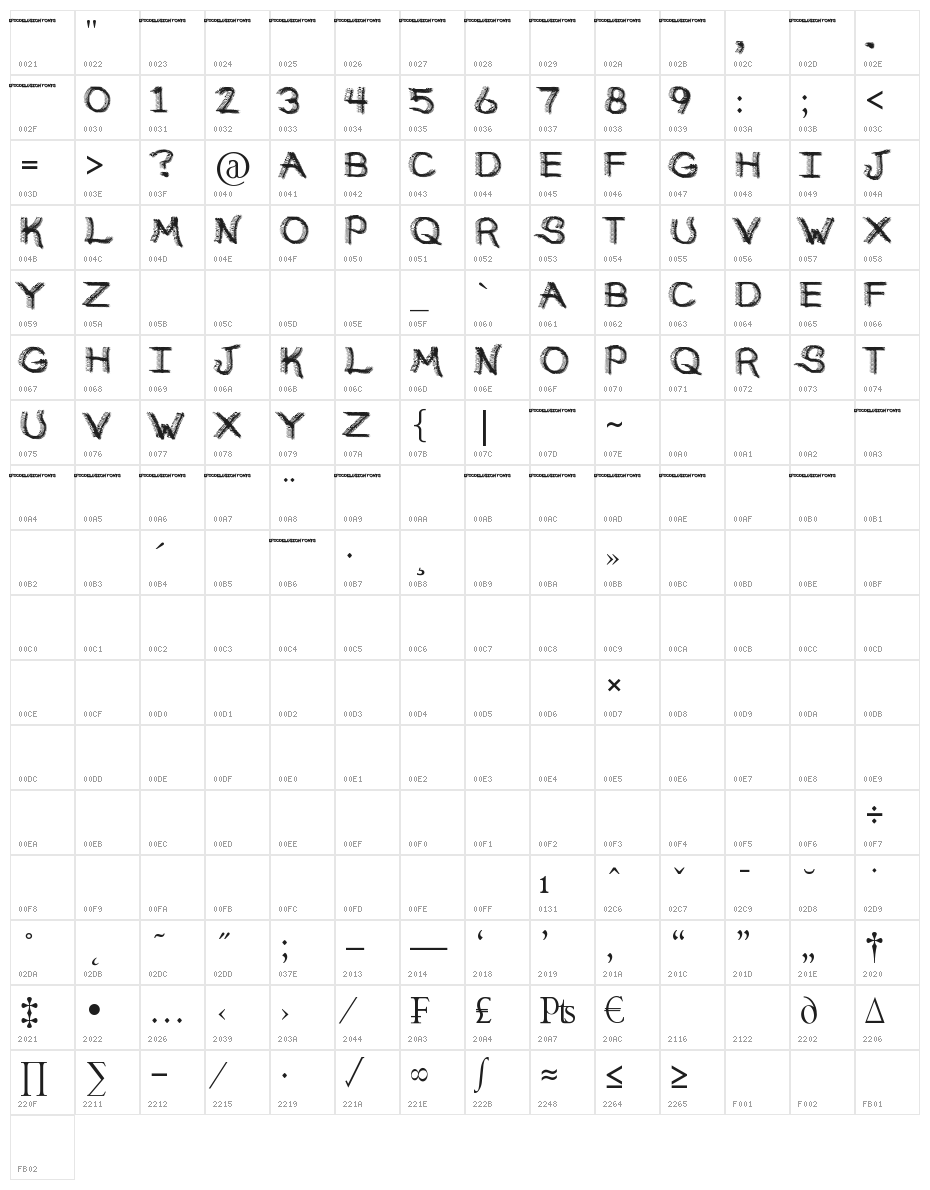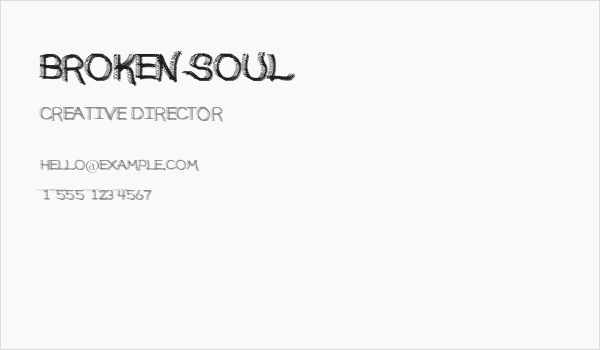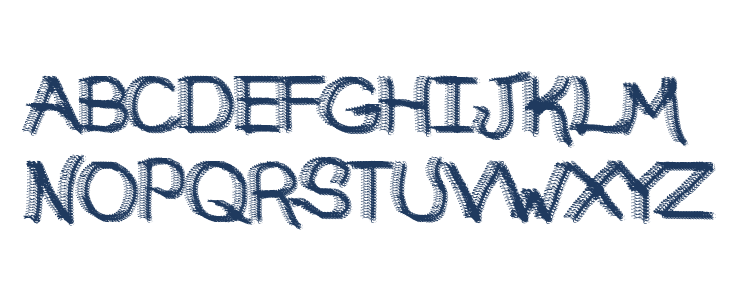
Broken Soul Font
✎ Distorted Eroded
| Progetti proposti | Ideal for album covers, posters, urban-themed designs, and branding that requires a bold, edgy look. |